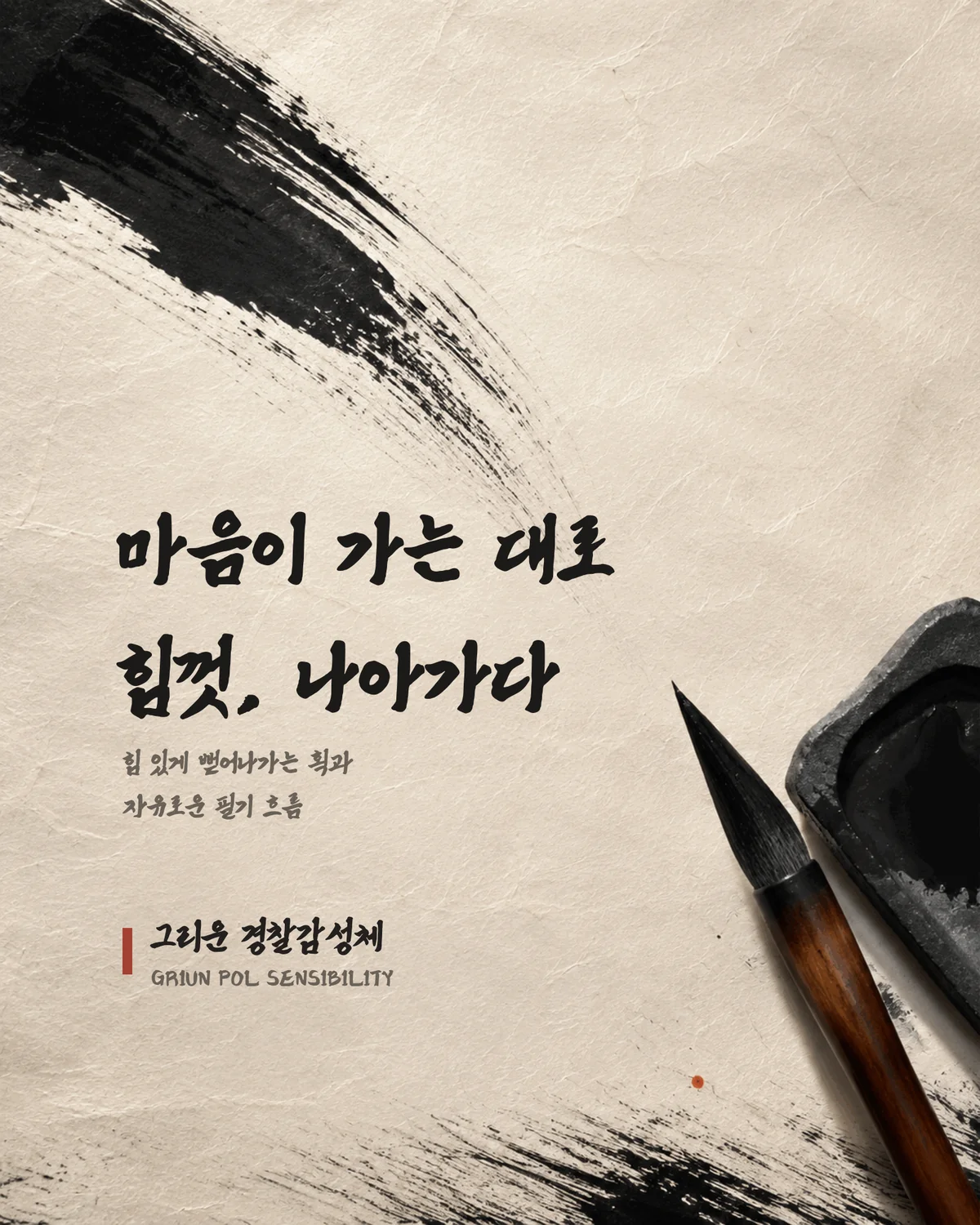
그리운 경찰감성체 — 서울경찰청 X 그리운에서 배포하는 무료 폰트입니다. 힘 있게 뻗어나가는 획과 자유로운 필기 흐름이 인상적인 붓글씨 계열 손글씨체
서울경찰청과 그리운이 함께 만들어 2025년에 배포한 서체입니다. 그리운은 개인의 손글씨를 폰트로 만들어 주는 서비스로, 무료 폰트도 여러 벌 배포하고 있습니다.
**서울경찰 인권손글씨 공모전 수상작**을 폰트로 옮긴 것입니다. 같은 공모전에서 나온 경찰인권체와 경찰공평체가 함께 있는데, 두 서체는 각각 현장경찰관과 새내기 경찰관의 글씨라고 밝혀져 있는 반면 이 서체는 글씨 주인의 신분이 공개돼 있지 않습니다.
만든 뜻과 조형을 한 문단으로 적어 두었습니다. 서로 다름을 이해하고 차별과 혐오를 넘어선 공감대 형성을 통해 공존의 세상으로 나아가기 위한 바람으로 제작되었으며, 수상작으로 선정된 이 글씨는 **자유와 연대를 향해 거리낌 없이 써 내려간 시원한 느낌의 필체**라는 것입니다.
파일에서 재어 보면 받침이 붙을 때 글자 높이가 달라지는 탈네모틀이고 자면을 꽤 채워 인상이 또렷합니다. 굵기는 하나이고 한글은 2,780자라 드문 음절은 빠질 수 있으니 어떤 글자가 올지 모르는 자리에는 미리 확인하고 쓰세요. 모든 사용 범위에서 자유롭게 쓸 수 있고 폰트 파일의 개작과 수정, 판매만 금지됩니다.